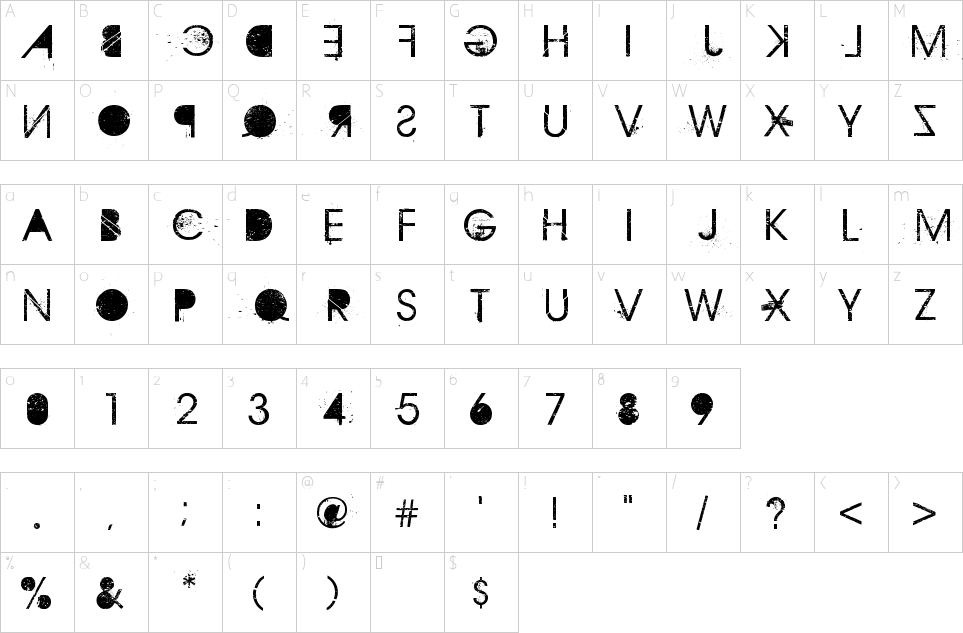
Aristotle Punk é uma fonte gráfica original, projetada cuidadosamente por um designer não identificado. Ela se destaca na categoria de fontes gratuitas com um estilo inconfundível, que mistura elementos futuristas e arquitetônicos em um único design. Seu uso pode trazer uma forte personalidade para qualquer projeto, seja em um logotipo atrevido e moderno, ou em um site com um design audacioso. As características elegantes e a consistência de estilo tornam Aristotle Punk uma escolha atraente para designers, tanto para aqueles que buscam um novo look para suas criações quanto para aqueles que valorizam uma fonte de alta qualidade sem custos. Com 14.403 downloads confirmados, é um recurso visual que já conquistou um grande número de usuários. Descubra agora mesmo como introduzir esta inconfundível presença de estilo à sua próxima projeto de design.